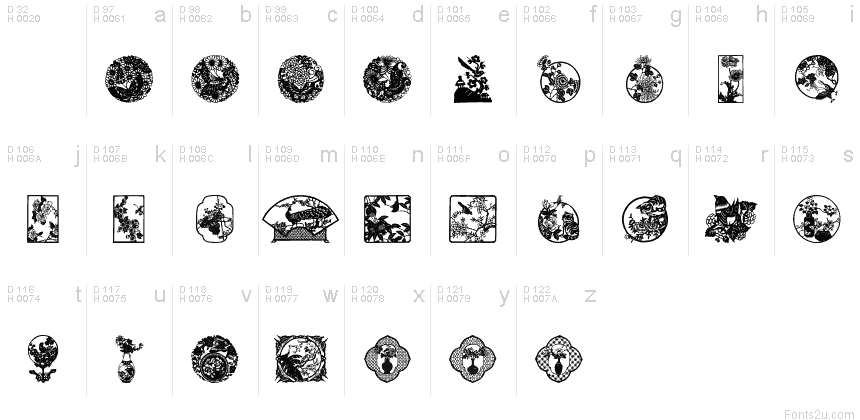
Шрифт Oriental View от House of Lime — это бесплатный декоративный гарнитур, состоящий из азиатских дингбатов: компактных иллюстраций птиц, цветов, веток и других мотивов в рамках. Эти знаки больше похожи на орнаментальные символы, чем на буквы, поэтому данное семейство шрифтов скорее служит набором графических акцентов, чем стандартным алфавитом.
Oriental View отлично подойдет для приглашений, упаковки, этикеток, плакатов и канцелярских товаров, если вы хотите, чтобы небольшое изображение несло в себе основной посыл. Этот бесплатный шрифт также пригодится для крафтовых проектов и декоративных заголовков, так как его пиктограммы сразу задают нужную тему без необходимости в дополнительных иллюстрациях.
Oriental View